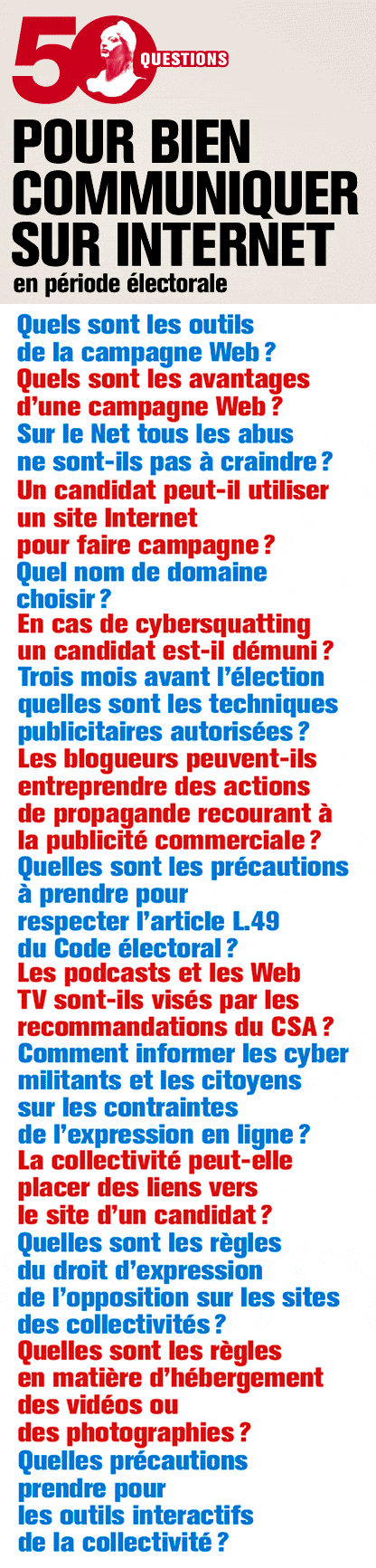
Lu dans le Monde d’aujourd’hui un billet circonstancié sur la légistlation électorale qui investit le champ des espaces interactifs. Un document PDF ci-dessous (sous l’image) pour avoir tous les détails. Où l’on voit qu’une typographie claire et sans prétention permet de faire passer un message juridique assez rébarbatif. Dommage que pour le traité constitutionnel on n’ait pas eu de documents aussi simples à déchiffrer.